Trong thiết kế, kiểu chữ không chỉ đơn giản là chọn một phông chữ thật đẹp mà còn giúp giao tiếp hiệu quả giữa thiết kế và người xem/ người sử dụng. Sự phong phú của Tiếng Việt cùng bộ dấu đi kèm đòi hỏi những phông chữ có thể thể hiện chính xác từng ký tự. Sử dụng phông chữ hỗ trợ tiếng Việt không chỉ đảm bảo tính rõ ràng mà còn tôn trọng cấu trúc độc đáo của ngôn ngữ.
Trong bài viết này, hãy cùng Align khám phá tầm quan trọng của việt chọn đúng font chữ phù hợp cho tiếng việt và điểm qua một số font Việt hoá có thể sử dụng trong thiết kế của bạn.
Tại sao nên sử dụng Font Việt Hoá trong thiết kế?
Sử dụng font Việt Hoá là rất quan trọng vì nhiều lý do sau đây:
1. Tiếng Việt đòi hỏi sự chính xác trong từ câu chữ
Tiếng Việt là một ngôn ngữ phức tạp với các dấu câu độc đáo có thể thay đổi ý nghĩa của từ ngữ. Font không hỗ trợ các dấu này có thể dẫn đến các ký tự sai, gây ra hiểu lầm. Ví dụ, từ “chao” có thể có nghĩa là “chào,” “cháo” hoặc “chảo” tùy thuộc vào các dấu được sử dụng. Font được hỗ trợ đúng cách đảm bảo mỗi từ được hiển thị chính xác, giữ nguyên ý nghĩa ban đầu.
2. Tăng Cường Khả Năng Đọc Hiểu Trong Thiết Kế
Khả năng đọc là rất quan trọng trong thiết kế, đặc biệt là trong nội dung văn bản. Font Việt Hóa đảm bảo tất cả văn bản dễ đọc bởi người bản xứ. Khi các ký tự không được hiển thị đúng, nó có thể tạo ra sự nhầm lẫn và giảm hiệu quả tổng thể của thông điệp. Font được hỗ trợ tốt duy trì tính toàn vẹn của văn bản, làm cho nó dễ dàng hơn cho khán giả để đọc và hiểu.
3. Chuyên Nghiệp và Đáng Tin Cậy
Sử dụng các font phù hợp hỗ trợ tiếng Việt thể hiện tính chuyên nghiệp và chú ý đến chi tiết. Điều này cho thấy designers tôn trọng ngôn ngữ và khán giả, tăng cường sự tin cậy của công việc. Ngược lại, việc sử dụng các font không hỗ trợ ngôn ngữ có thể trông thiếu cẩn thận và không chuyên nghiệp, có thể ảnh hưởng đến uy tín và độ chuyên nghiệp của designer.
4. Cải Thiện Trải Nghiệm Người Dùng
Một trải nghiệm người dùng mượt mà là mục tiêu chính trong thiết kế. Font Việt Hoá đóng góp vào trải nghiệm đọc mượt mà hơn và dễ chịu hơn cho người dùng. Khi văn bản rõ ràng và được hiển thị chính xác, nó giảm tải nhận thức, cho phép người dùng tham gia sâu hơn với nội dung.
5. Tính Linh Hoạt Trong Thiết Kế
Sử dụng font Việt hoá mở ra nhiều khả năng thiết kế hơn. Nhà thiết kế có thể tự tin tạo ra nhiều loại nội dung khác nhau, từ trang web và ứng dụng di động đến tài liệu in ấn và quảng cáo, biết rằng văn bản của họ sẽ được hiển thị đúng. Tính linh hoạt này đặc biệt quan trọng đối với các thương hiệu và doanh nghiệp muốn tiếp cận thị trường nói tiếng Việt.
6. Tuân Thủ Tiêu Chuẩn Ngôn Ngữ
Trong một số trường hợp, sử dụng font hỗ trợ ngôn ngữ địa phương không chỉ là một thực hành tốt mà còn là một yêu cầu. Tài liệu chính thức, tài liệu giáo dục và một số loại quảng cáo nhất định phải tuân thủ các tiêu chuẩn ngôn ngữ, bao gồm việc đại diện chính xác tất cả các ký tự. Sử dụng font chính xác đảm bảo tuân thủ các tiêu chuẩn này.
Top Font Việt Hoá Trong Thiết Kế
Chọn đúng font là rất quan trọng khi thiết kế cho khán giả Việt Nam. Dưới đây là một số font được khuyến nghị cao, không chỉ hỗ trợ ký tự tiếng Việt mà còn nâng cao thẩm mỹ tổng thể của thiết kế. Mỗi font mang đến phong cách và chức năng độc đáo, làm cho chúng phù hợp với nhiều dự án thiết kế khác nhau.
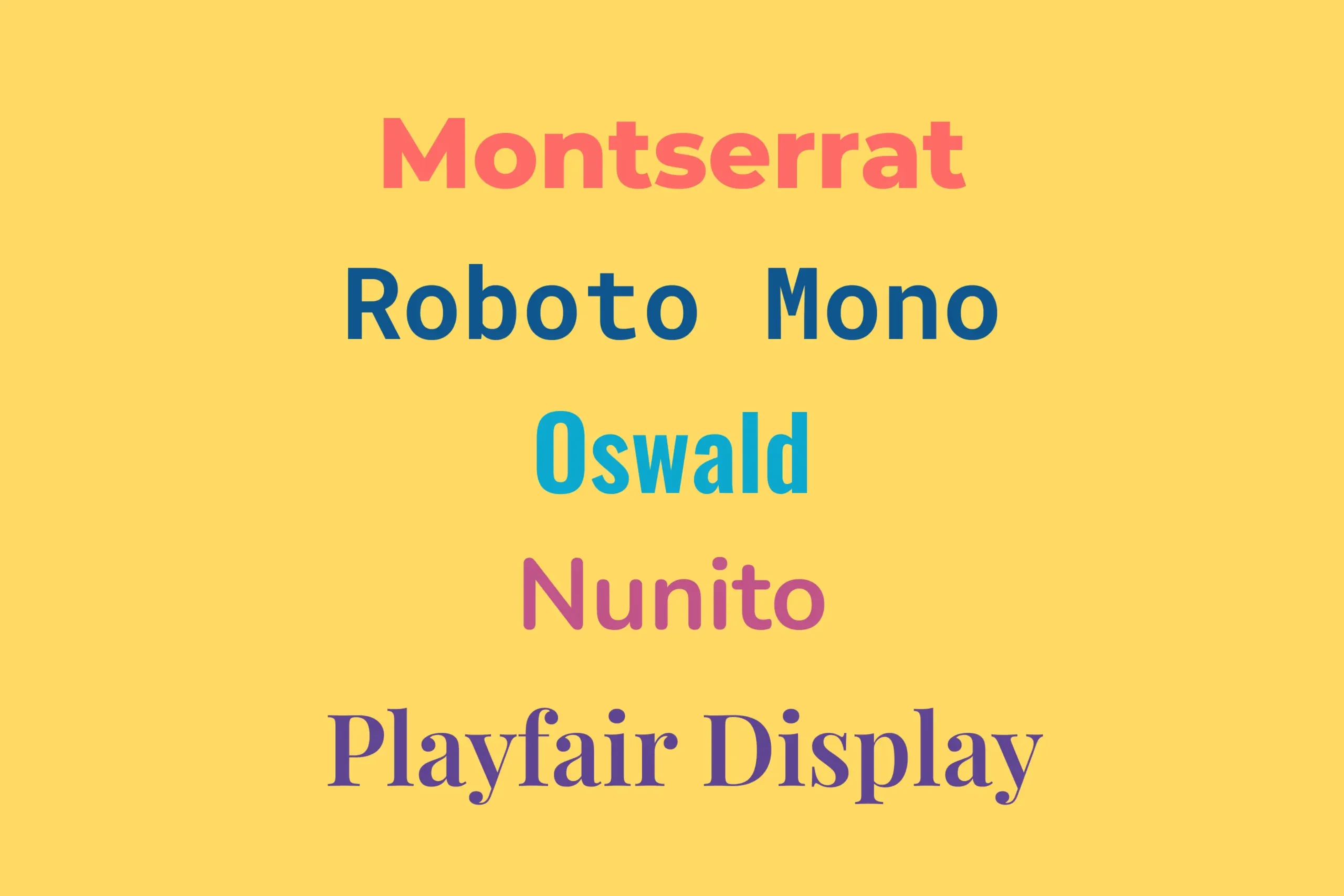
1. Montserrat
Montserrat là một kiểu chữ sans-serif hiện đại và đa dụng, lấy cảm hứng từ kiểu chữ đô thị từ khu phố Montserrat của Buenos Aires. Nó hỗ trợ tốt cho các ký tự tiếng Việt, đảm bảo khả năng đọc và sự tinh tế. Với nhiều trọng lượng và kiểu dáng khác nhau, Montserrat hoàn hảo cho cả tiêu đề và văn bản thân. Montserrat thường được sử dụng trong thiết kế web, thương hiệu và bố cục biên tập, mang lại vẻ sạch sẽ và chuyên nghiệp.
2. Roboto Mono
Roboto Mono là một kiểu chữ monospaced thuộc gia đình Roboto. Nó duy trì thiết kế sạch sẽ và rõ ràng, làm cho nó lý tưởng cho mã hóa, tài liệu kỹ thuật và bất kỳ dự án nào yêu cầu font cố định chiều rộng. Roboto Mono hỗ trợ ký tự tiếng Việt, đảm bảo rằng các dự án kỹ thuật và kỹ thuật số của bạn đều có tính năng và thẩm mỹ hấp dẫn.
3. Oswald
Oswald là một sự tái hiện lại phong cách kiểu chữ gothic cổ điển, với một nét hiện đại. Nó hỗ trợ các ký tự tiếng Việt và thường được sử dụng cho các tiêu đề đậm và các tuyên bố ấn tượng. Tính chất cô đặc của nó cho phép nhiều văn bản trong không gian nhỏ hơn mà không làm giảm khả năng đọc. Oswald hoàn hảo cho các poster, quảng cáo và bất kỳ thiết kế nào yêu cầu văn bản mạnh mẽ và thu hút sự chú ý.
4. Nunito
Nunito là một kiểu chữ sans-serif cân đối với các đầu tròn, mang lại vẻ thân thiện và dễ gần. Nó hỗ trợ các ký tự tiếng Việt, làm cho nó phù hợp với nhiều ứng dụng khác nhau, từ trang web đến tài liệu in ấn. Tính dễ đọc và ấm áp của Nunito làm cho nó trở thành lựa chọn tuyệt vời cho văn bản thân và tiêu đề trong tài liệu giáo dục, blog và giao tiếp doanh nghiệp.
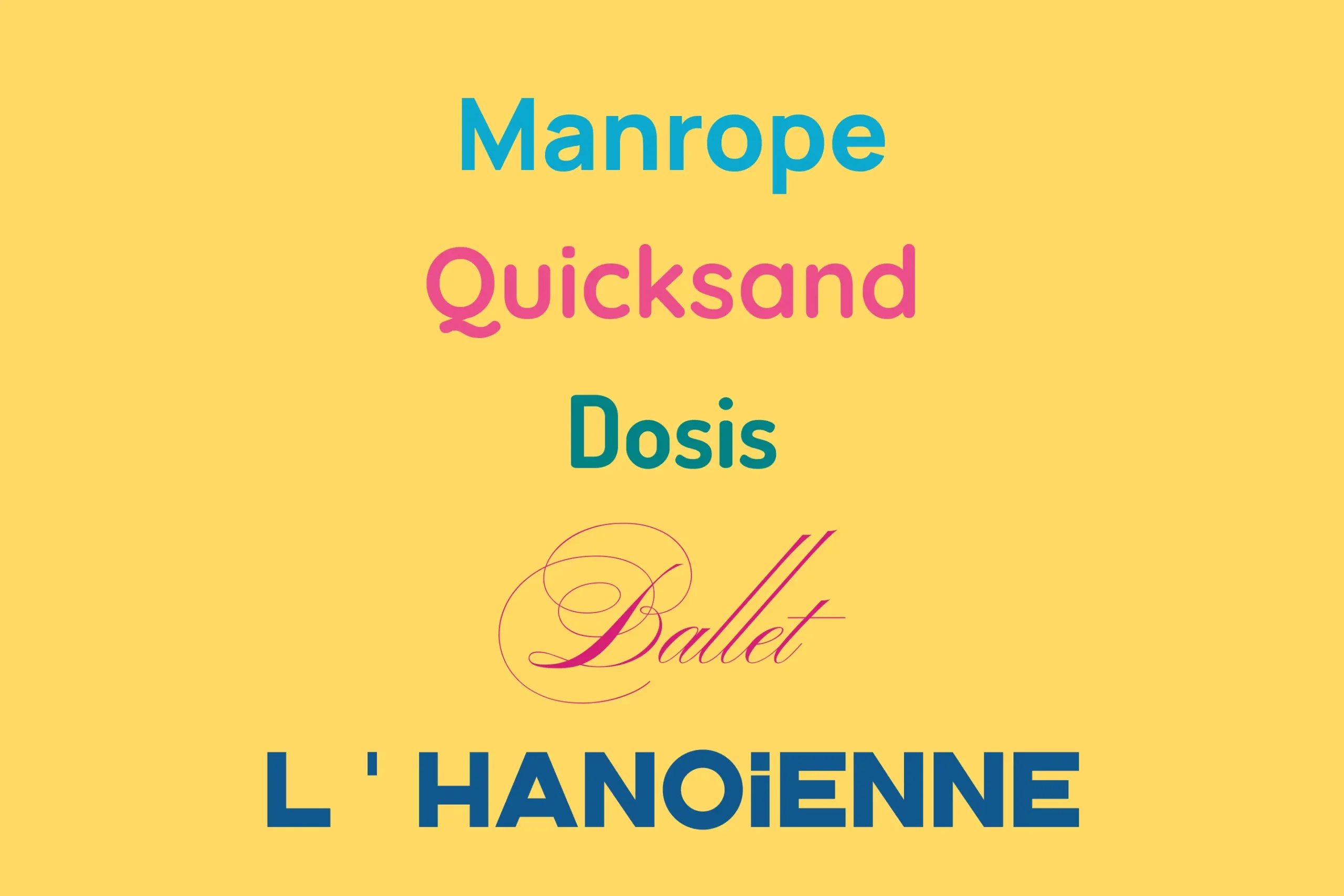
5. Playfair Display
Playfair Display là một kiểu chữ serif tỏa ra sự thanh lịch và tinh tế. Nó hỗ trợ các ký tự tiếng Việt và lý tưởng cho thiết kế biên tập, tiêu đề và bất kỳ dự án nào cần một chút sự tinh tế cổ điển. Sự tương phản cao và phong cách đặc trưng của Playfair Display làm cho nó hoàn hảo cho bìa tạp chí, tiêu đề sách và thương hiệu sang trọng.
6. Manrope
Manrope là một kiểu chữ sans-serif hình học hiện đại được thiết kế với sự đơn giản và tinh tế. Nó hỗ trợ nhiều ngôn ngữ, bao gồm tiếng Việt, làm cho nó trở thành một lựa chọn đa năng cho các dự án thiết kế khác nhau. Manrope rất phù hợp cho giao diện người dùng, thương hiệu doanh nghiệp và các thiết kế tối giản nơi mà sự rõ ràng và đơn giản là quan trọng nhất.
7. Quicksand
Quicksand là một kiểu chữ sans-serif với các góc bo tròn, được thiết kế cho mục đích hiển thị. Nó hỗ trợ các ký tự tiếng Việt và hoàn hảo cho các dự án thiết kế thân thiện và dễ gần. Vẻ ngoài hiện đại và vui tươi của nó làm cho nó lý tưởng cho sách thiếu nhi, bao bì sản phẩm và trang web sáng tạo, mang lại vẻ nhẹ nhàng nhưng chuyên nghiệp.
8. Dosis
Dosis thuộc hệ font sans-serif đơn giản và tròn, hỗ trợ các ký tự tiếng Việt. Nó thường được sử dụng cho các thiết kế tối giản và hiện đại, mang lại vẻ ngoài sạch sẽ và đơn giản. Dosis rất tuyệt vời cho các startup công nghệ, đồ họa thông tin và nội dung kỹ thuật số, nơi mà sự rõ ràng và hiện đại là cần thiết.
9. Ballet
Ballet là một kiểu chữ thanh lịch và phong cách, hỗ trợ các ký tự tiếng Việt. Các đường cong duyên dáng và vẻ ngoài tinh tế của nó làm cho nó hoàn hảo cho các dự án sáng tạo và nghệ thuật. Ballet lý tưởng cho thương hiệu thời trang, thiệp mời và bất kỳ thiết kế nào tìm cách gợi lên cảm giác thanh lịch và đẹp đẽ.
10. L’Hanoienne Free Typeface
L’Hanoienne Free Typeface được thiết kế đặc biệt với hỗ trợ đa ngôn ngữ, bao gồm tiếng Việt. Được tạo bởi nhà thiết kế Mạnh Nguyễn, kiểu chữ này mang đến một lựa chọn độc đáo và giàu văn hóa cho các nhà thiết kế muốn kết hợp các yếu tố Việt Nam chân thực vào công việc của họ. Nó kết hợp giữa thẩm mỹ truyền thống của Việt Nam với các nguyên tắc kiểu chữ hiện đại, làm cho nó phù hợp cho các dự án văn hóa, thương hiệu di sản và thiết kế nghệ thuật.
Kết luận
Chọn đúng font cho thiết kế ngôn ngữ tiếng Việt là rất cần thiết cho khả năng đọc, thẩm mỹ và nhạy cảm văn hóa. Các font được liệt kê ở trên cung cấp sự hỗ trợ tuyệt vời cho các ký tự tiếng Việt, đảm bảo rằng các thiết kế của bạn vừa chức năng vừa đẹp mắt. Cho dù bạn đang làm việc trên một trang web hiện đại, một thiết kế biên tập thanh lịch, hay một dự án sáng tạo, những font này sẽ giúp bạn truyền tải thông điệp một cách hiệu quả đến khán giả nói tiếng Việt.